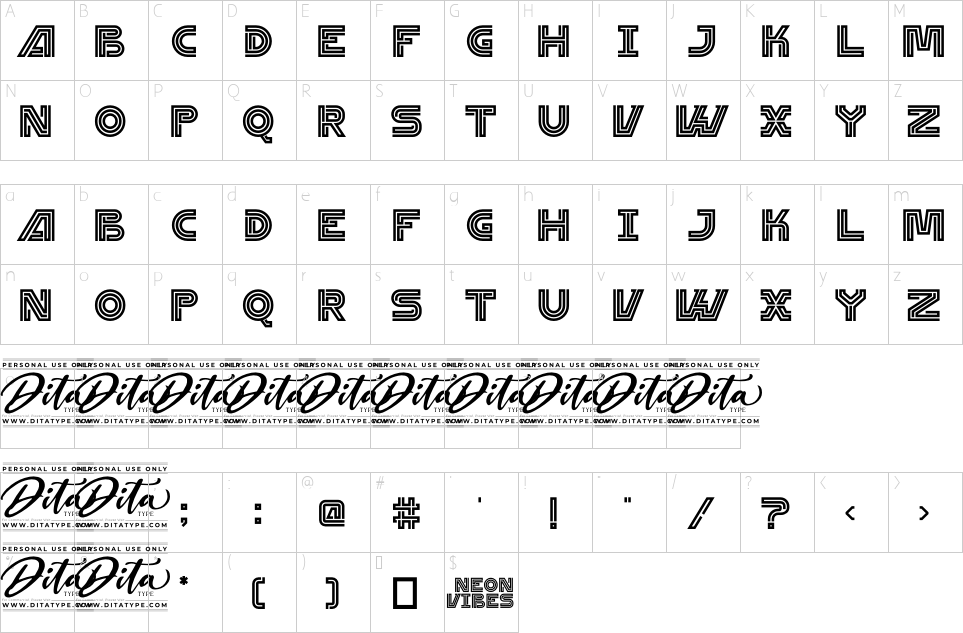
Neon Vibes Font – Download Grátis
A Neon Vibes é uma fonte artística que combina elementos modernos e futuristas em um único design. Ela foi criada pelo designer Dita Type e apresenta uma aparência vibrante e iluminada, perfeita para criar efeitos visuais noturnos ou ambientes tecnológicos ao seu site ou aplicativo. Composta de linhas curvas e formas geométricas, esta fonte traz um toque único à qualquer projeto, seja ele digital ou impresso. Esta fonte é especialmente atraente quando usada em textos chamativos ou gráficos interativos. Se você está buscando uma maneira criativa de destacar o seu trabalho em uma atmosfera neon e tecnológica, a Neon Vibes será um ótimo complemento para seus projetos digitais. Sua versatilidade a torna perfeita tanto para aplicativos móveis quanto para websites, garantindo que seu design seja notado nas sombras da web.